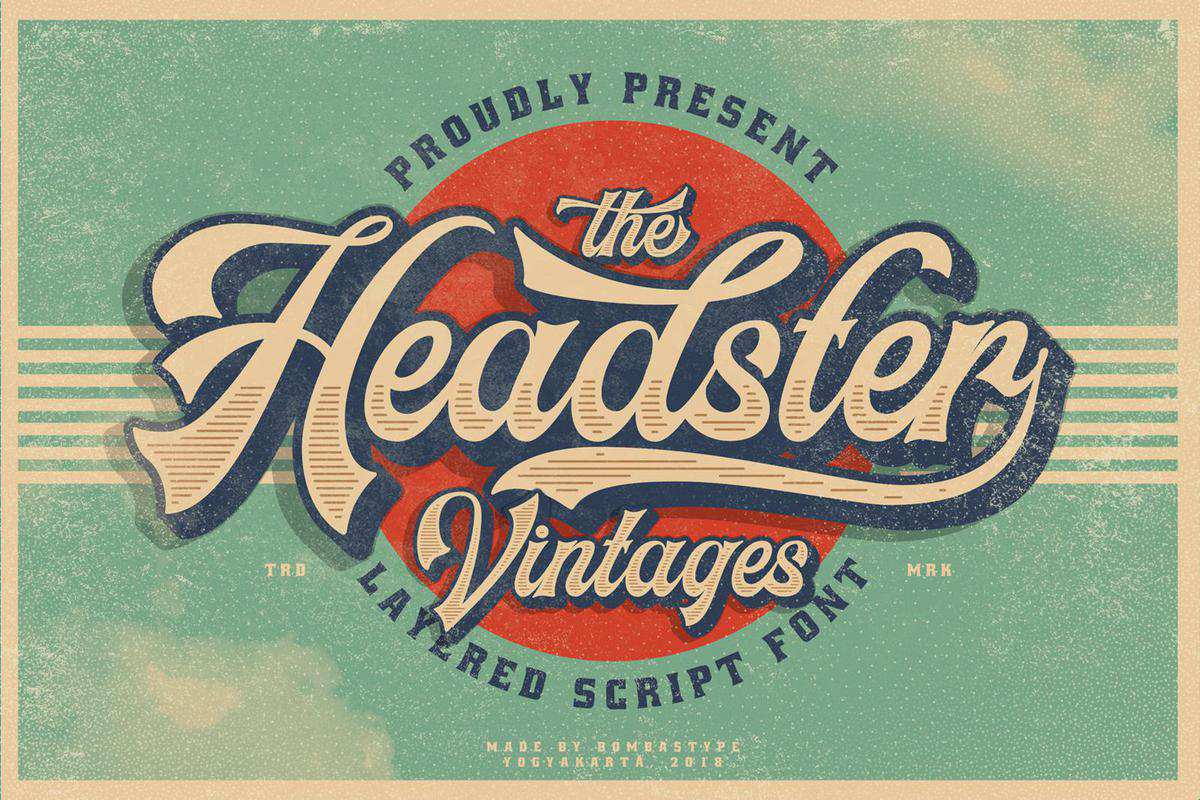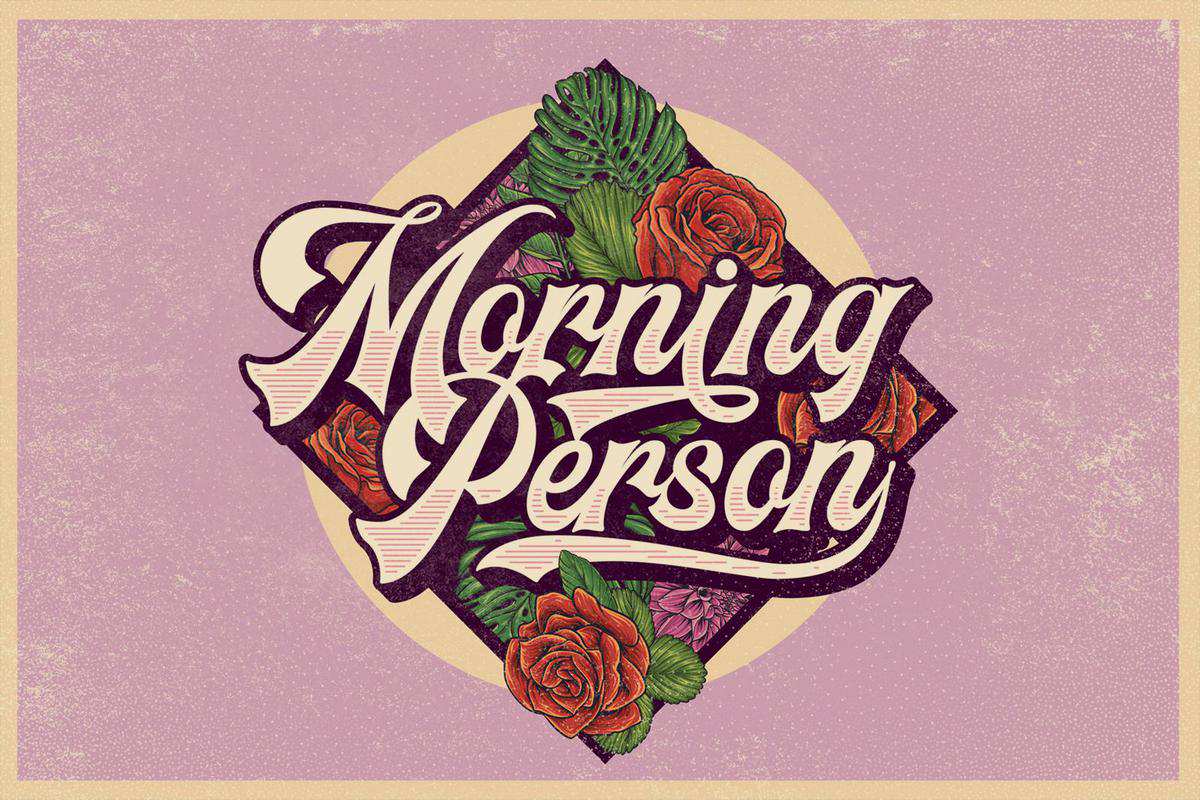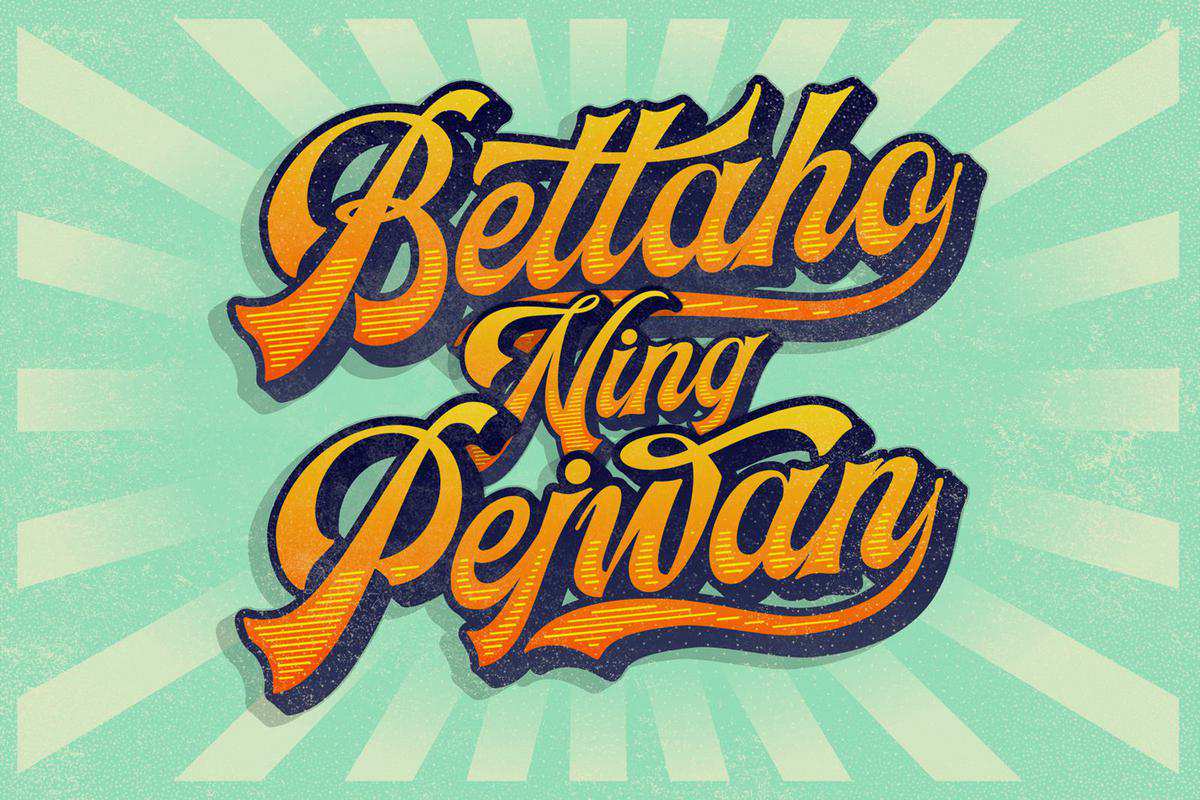
简介受Vintagelabeldesigns启发的黑体字体Facet。采用分层系统,05fontstotal。具有多种可播放的交互特征。您可以混合和匹配您的最佳组合。通过我们提到的所有内容,该字体非常适合您的许多设计项目,如传单、标志设计、徽章、包装、邀请等等。简介,BoldScripttypeFaceFaceDaceDaceDa。